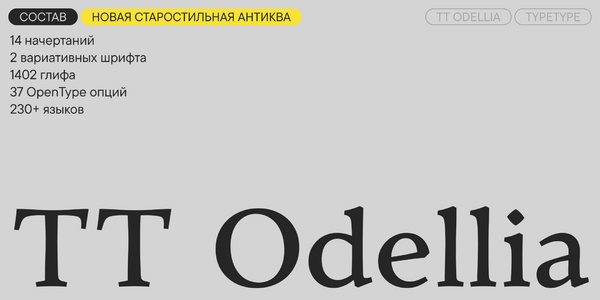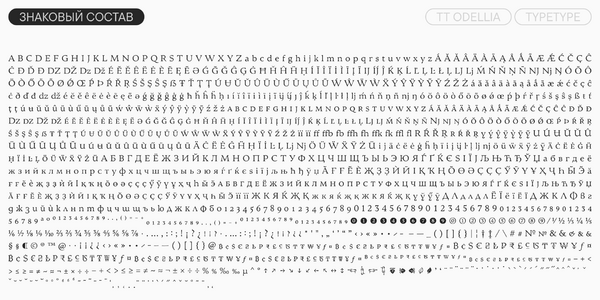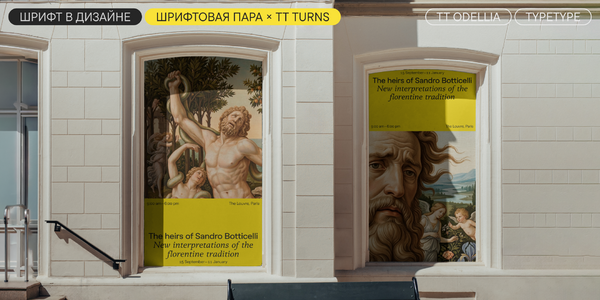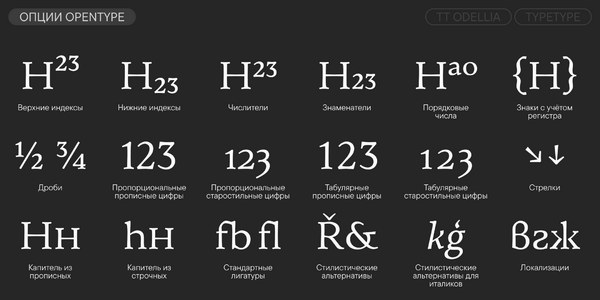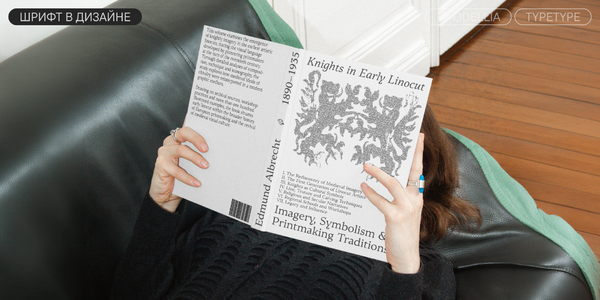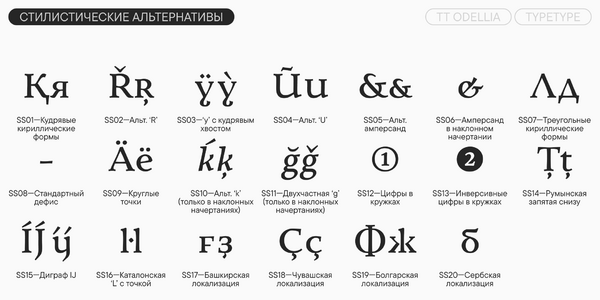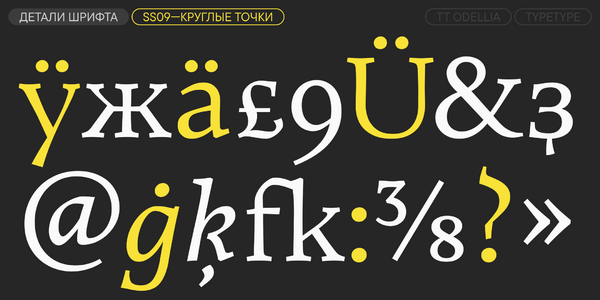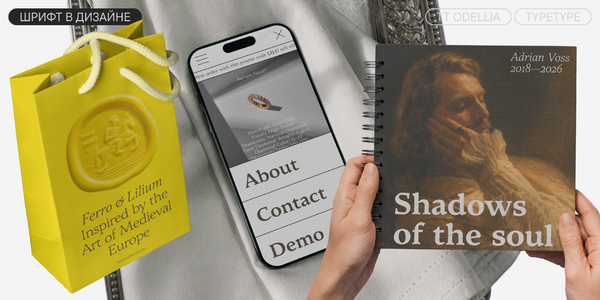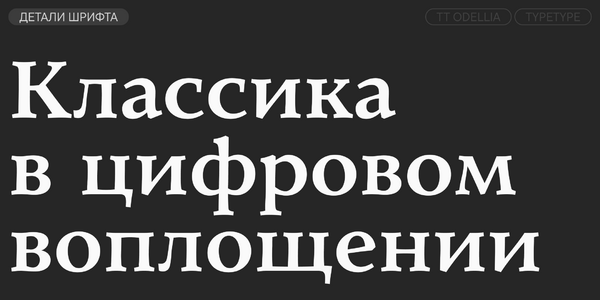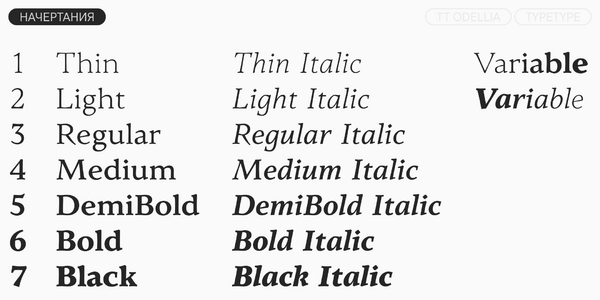
TT Odellia
TT Odellia — ТТ Оделлия
Произносится «ТТ Оделлия». Слово «Odellia» — производное от имён Одетта и Одиллия из балета «Лебединое озеро». Буквы TT являются аббревиатурой названия компании.
TT Odellia — старостильная антиква с современным рисунком, вдохновлённая венецианскими шрифтами и классической музыкой.
TT Odellia — старостильная антиква, выполненная современными инструментами
Шрифтовая гарнитура TT Odellia — долгожданный релиз нашей студии. Шрифт создавался в течение трёх лет и представляет собой старостильную антикву, выполненную в авторской манере. Название вдохновлено балетом «Лебединое озеро» и является производным от имён его героинь — Одетты и Одиллии. Партии Одетты и Одиллии в балете раскрывают двойственность человеческой натуры через контраст добра и зла. Одетта, белый лебедь, символизирует чистоту, нежность и уязвимость, тогда как Одиллия, чёрный лебедь, — коварство, силу и соблазн. В шрифте эта двойственность прочитывается как сочетание мягкой, рукотворной старостильной антиквы с чистотой и подвижностью контуров, доступными только в векторном формате XXI века.
«Лебединое озеро» — балет Петра Ильича Чайковского, написанный в 1876 году, в четырёх актах.
В шрифте 1399 знаков и 20 стилистических сетов.
О гарнитуре TT Odellia
Встречайте новый TT Odellia — первую старостильную антикву в коллекции TypeType, вдохновлённую венецианскими шрифтами и классической музыкой.
TT Odellia — старостильная антиква с современным рисунком. Это долгожданный релиз нашей студии: шрифт создавался в течение трёх лет. Он не повторяет классические образцы венецианских антикв: это их собирательный образ в современной интерпретации.
TT Odellia представляет собой единство противоположных начал: динамика и подвижность стемов в сочетании с чётко очерченными формами и яркими засечками демонстрируют воплощение рукотворной идеи в цифровом формате. Это отражается в названии гарнитуры: в нём слились имена Одетты и Одиллии — героинь балета «Лебединое озеро», белого и чёрного лебедей. Их образы символизируют двойственность человеческой натуры через контраст добра и зла.
Классический вид TT Odellia дополняется ромбовидными точками и дефисами, выполненными под наклоном. Для более современного звучания их можно заменить на привычные формы. Альтернативные ‘Ж’, ‘К’, ‘Я’, ‘R’ позволяют сделать шрифт мягким и дружелюбным или более нейтральным. Поиграть в историзм помогают альтернативные ‘y’, ‘U’, а также набор треугольных ‘Д’, ‘д’ и ‘Л’, ‘л’. Кириллица в шрифте отличается самобытным рисунком благодаря формам основных знаков ‘б’, ‘д’, ‘л’ и ‘з’, ‘э’ с вертикальными засечками.
Курсивные начертания отличаются от прямых. Благодаря более узким пропорциям и оригинальным формам курсив хорошо работает в паре с прямым начертанием: он контрастирует с ним, что позволяет расставлять акценты в тексте. И в то же время его можно использовать в качестве полноценного текстового шрифта.
TT Odellia изначально разрабатывался как текстовый шрифт. Невысокий контраст, открытая апертура и динамичные формы обеспечили ему превосходную читабельность даже в размере 6–8 пт. Однако благодаря выразительному рисунку он прекрасно работает и в заголовках. Шрифт подойдёт для разных сфер: например, для проектов, связанных с музыкой, историей и искусством. Он может стать рабочей лошадкой для набора текста в художественно-литературных изданиях, вёрстки меню и оформления этикеток.